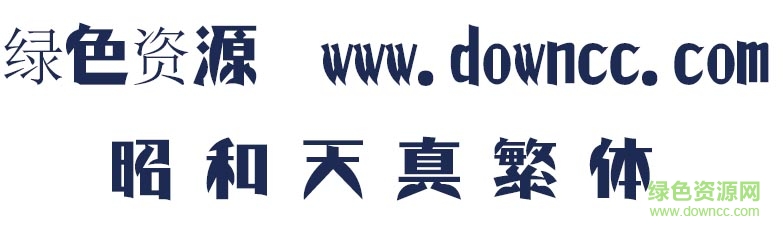
軟件介紹 軟件標簽: 昭和字體 日本字體 字體 昭和天真繁體字體是一款外面很多伙伴想找的一款日本昭和字體,這款字體形態(tài)優(yōu)美,看著非常舒服,所以大家如果也需要這款字體的話,那就快來綠色資源網(wǎng)下載吧昭和天真繁體字體欣賞:昭和天真繁體安裝方法:方法一:控制面板/字體/文件/安裝新字體;方法二:直接將字體復制到C:\WINDOWS\Fonts。方法三:針對win7系統(tǒng),用戶只需選中字體右鍵安裝即可。注意事項:本站所有字體資源僅供個人學習與參考,如需商業(yè)使用請到相關(guān)官網(wǎng)授權(quán)。 軟件截圖 上一張下一張(1 / 1) 安裝詳細截圖 猜你喜歡 繁體字體 日文字體 繁體字體 繁體字體有哪些?小編今天為大家推薦幾款好看的繁體字體,包含了繁體鋼筆字體、繁體隸書字體、繁體毛筆字體、繁體行楷字體等不同類型的繁體字體!廣告、PPT、海報、雜志等領(lǐng)域都可使用! 查看更多>> wow魔獸世界臺服字體包 2.40M/中文/0.0/ttf免費版下載 繁體書法字體 3.41M/中文/6.6/下載 楷書繁體字體包 9.76M/中文/8.0/下載 隸書繁體字體 5.46M/中文/4.2/.ttf下載 茶碗古刻繁體 5.37M/中文/5.0/下載 hyx4gf regular 3.41M/中文/8.0/下載 日文字體 日文字體是一類日系風格的書法字體,日本文化起源于中華唐朝,延續(xù)了華夏文明的底蘊,同時也加入自己的本國特色,綠色資源網(wǎng)提供日本字體大全,歡迎大家下載使用! 查看更多>> hgp明朝e 320KB/中文/1.2/下載 hgp明朝b 350KB/中文/2.2/下載 ksw般若お試し教育漢字 2.44M/中文/5.0/下載 FGPイワタ細教科書體 2.98M/中文/5.0/下載 游教科書體字體 4.11M/中文/7.5/下載 紫羅蘭永恒花園京紫文字體 21KB/中文/5.0/ttf下載 其他版本下載 標題 大小 更新日期 下載 下載地址 電腦版 昭和天真繁體字體 ttf 點擊報錯 軟件無法下載或下載后無法使用,請點擊報錯,謝謝! 關(guān)閉報錯反饋 請描述您所遇到的錯誤,我們將盡快予以修正,謝謝! *必填項,請輸入內(nèi)容 本類最新 dreamweaver字體庫 首爾南山體字體 v1.06 官方版 潮字社風云簡ttf 潮字社凌渡鯤鵬簡體字體 潮字社曾玉波手書簡字體 微博慧心字體 相關(guān)文章 Photoshop字體安裝使用方法和技巧 如何解決“無法新增字體”問題 Win 7系統(tǒng)安裝字體方法 網(wǎng)頁字體大小設置方法 怎么改網(wǎng)頁字體大小 在Linux系統(tǒng)中安裝字體的幾種方法 windows7字體顯示問題:打開某些程序的時候顯示的是亂碼 用戶評論 熱門評論 最新評論 發(fā)表評論 查看所有評論(0) 昵稱: 請不要評論無意義或臟話,我們所有評論會有人工審核. 字數(shù): 0/500 (您的評論需要經(jīng)過審核才能顯示)